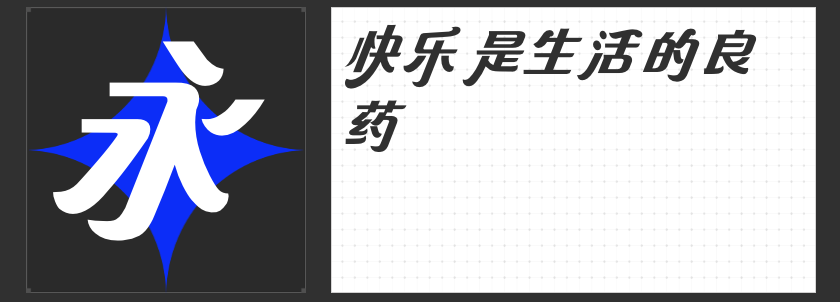
清新风格设计必备:四款精选字体推荐
在追求设计作品清新脱俗的今天,选择一款合适的字体显得尤为重要。字体不仅能够传达信息,更能营造出独特的视觉氛围。今天,就为大家推荐四款专为清新风格设计而生的字体,它们各具特色,能够为您的设计作品增添一抹别样的风采。
这款字体字形结构端正,笔画清晰,整体风格清秀别致。它的应用范围相当广泛,无论是短视频的字幕、海报的标题,还是各类宣传材料,都能轻松驾驭。字青春悸动简 常规的清新气质,能够为设计作品带来一股青春活力,让人眼前一亮。
造字侠郝刚快乐简 微黑采用中西结合的设计手法,巧妙地将西文斜体装饰风格的浪漫优雅与汉字隶书笔画的撇、捺错落变化融为一体。字体倾斜112度,蚕头燕尾的韵味中透露出斜体字的韵律感和节奏感。这款字体在微妙的平衡感中创造了轻松明快的自洽节奏,是对字体美感均衡把控的典范。
小豆岛默陌肥圆手写简以其丰腴圆润的字形和轻松自由的水墨笔触,治愈着一切不开心。笔画的节点随性而不拘小节,使得这款字体在应用中显得尤为灵活多变。无论是拉伸使用还是保持原样,都能展现出其独特的韵味和治愈系的气质。
四、小豆岛默陌秀丽简
小豆岛默陌秀丽简则是一款能够纵情释放文艺气息的字体。笔锋有力,疏密有致,它借鉴了传统书法的写意风格,点划看似随意却暗含章法。通过节奏的塑造,线条的粗细和节点得以完美呈现,使得整款字体在清新脱俗中透露出深厚的文化底蕴。
这四款字体各具特色,共同构成了清新风格设计的字体宝库。无论您是设计师还是普通用户,都能在这些字体中找到心仪的选择,为您的作品增添一份独特的韵味和气质。